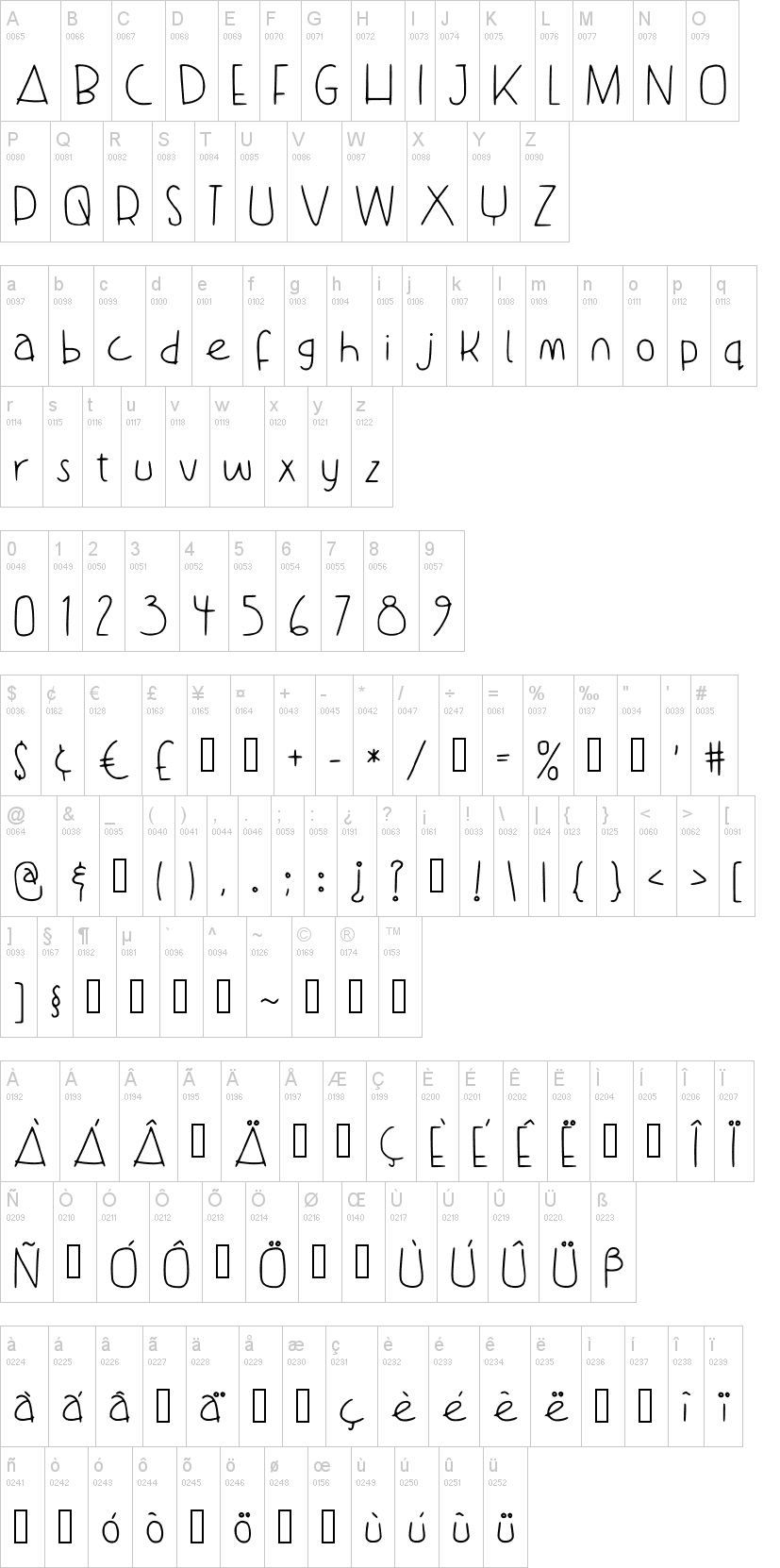
Dance With Me Tata 是一款由美国设计师Tara McPherson创作的手写体字体。该字体采用清新、柔和的线条,可以带给人们温馨的感觉。它具有独特的设计风格,能够搭配出优雅的文字效果。它的字形简洁,具有流畅的笔画,让文字充满活力和活泼的气息。此外,它还具有良好的可读性,可以让您的文字更加简洁明了。内容介绍
Dance With Me Tata是一款非常不错的手写艺术字体,具有很好的视觉感,适合于文化类的宣传设计、商业类品牌的广告和产品包装设计以及个性化文字排版等较多场景。